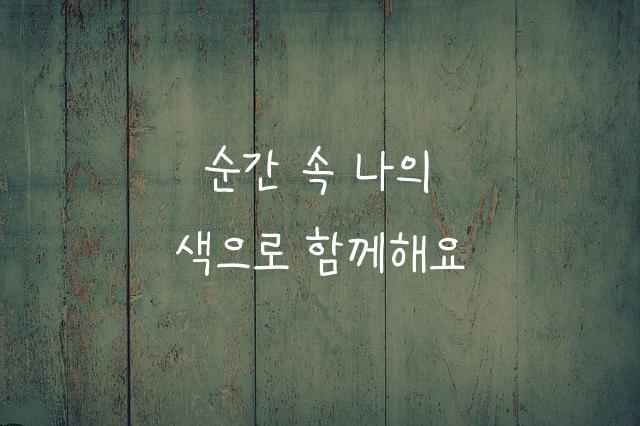
가시가시체 백민주는 스스로넷에서 제작한 독특하고 각진 손글씨 폰트입니다. 이 폰트는 개성 있는 디자인과 강렬한 인상을 남기는 데 최적화되어 있습니다.
가시가시체 백민주은(는)
손글씨, 네모꼴, 감성적인, 단단함 계열의 생김새를 가지고 있으며
포스터, 광고 캠페인 등에서 자주 활용되며, 효과적인 메시지 전달에 적합합니다.
이 폰트는 광고/마케팅, 크리에이티브 분야에 잘 어울리며,
창의적인, 강렬한 느낌을 담고 있는 것이 특징입니다.